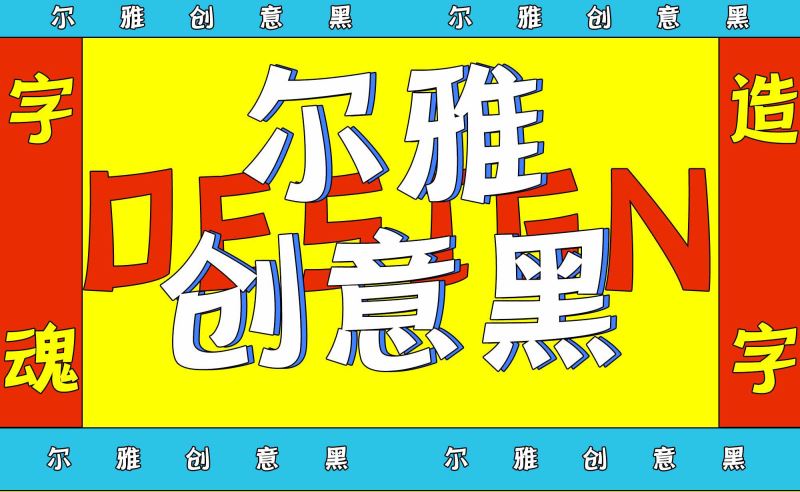
尔雅创意黑是尔雅家族的一 款脑洞大开的字体 。 “ 尔 ” 是 “ 近 ” 的 意思,“雅”是“正”的意思,尔雅便代表着合乎规范;创意却代表着破旧迎新。尔雅遇上创意,场守旧与叛离的⻆逐就此展开!
尔雅创意的笔画由右向左逐渐变粗、由上至下逐渐变细,笔势微微倾斜,笔顺虽直、笔画却曲,实现了尔雅与创意的完美交融!这款字的守成与叛逆使之可以适用于多种场景,一份菜单、一张海报、一本杂志、亦或是某个店装修……尔雅却不显呆板,创意却不乏温情。